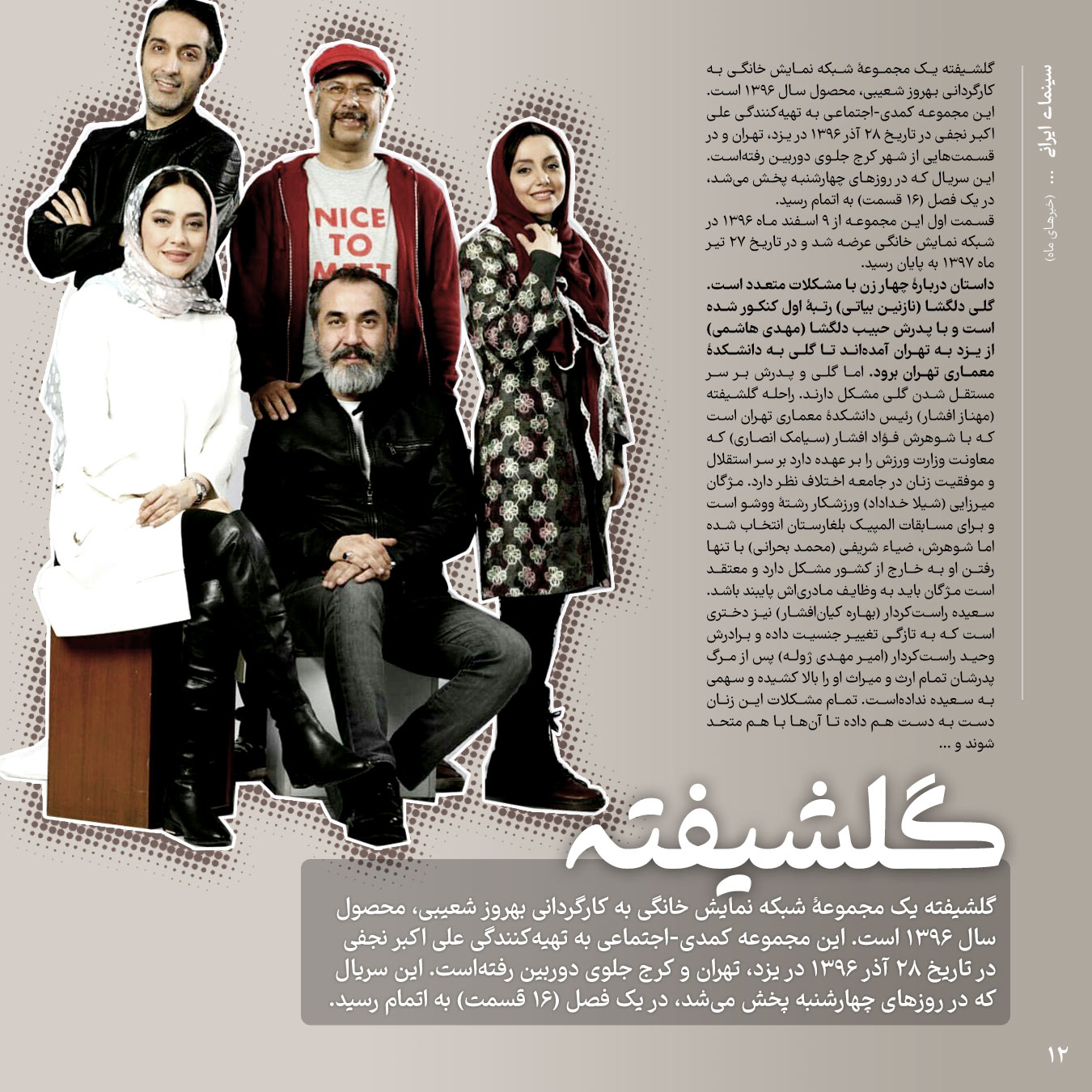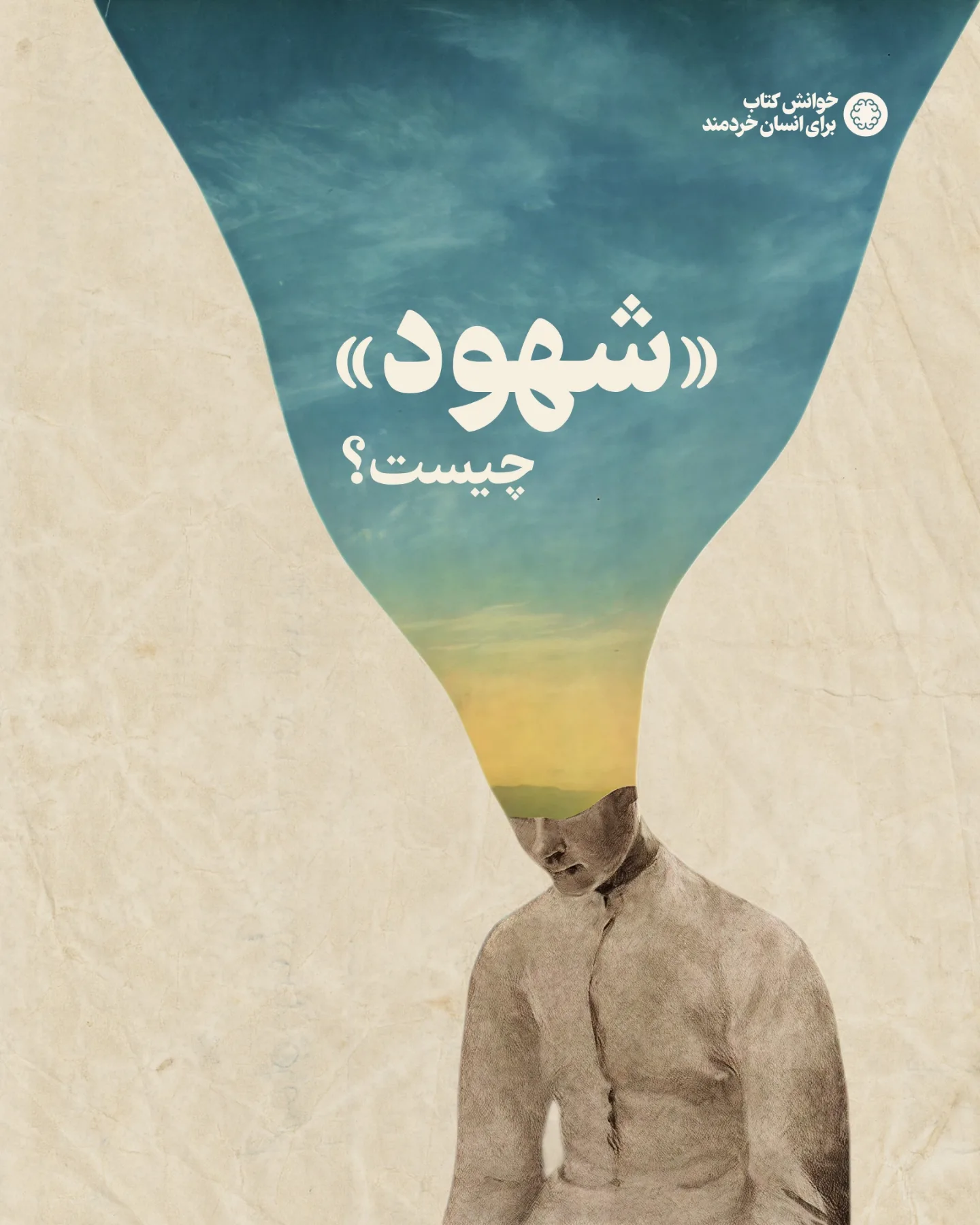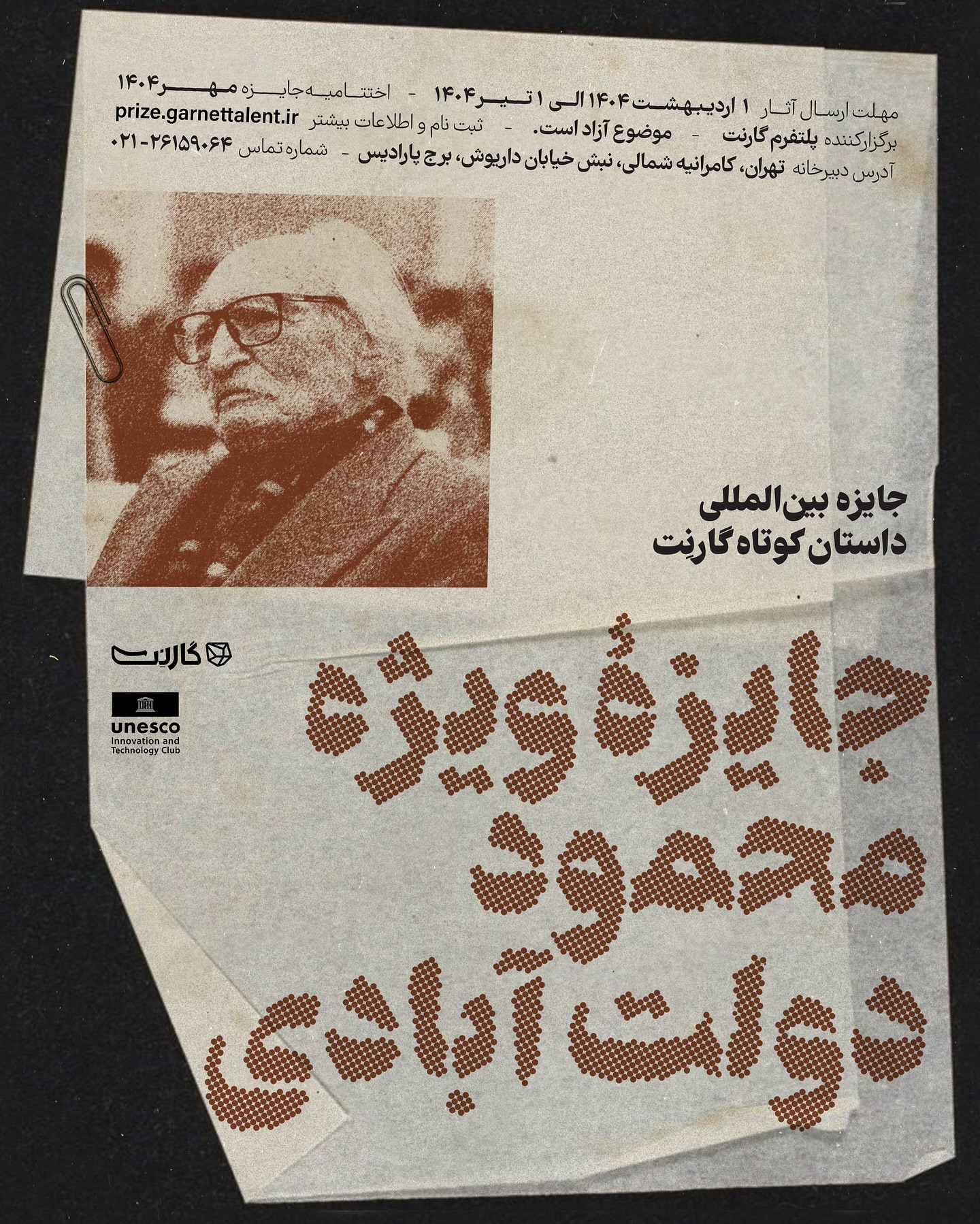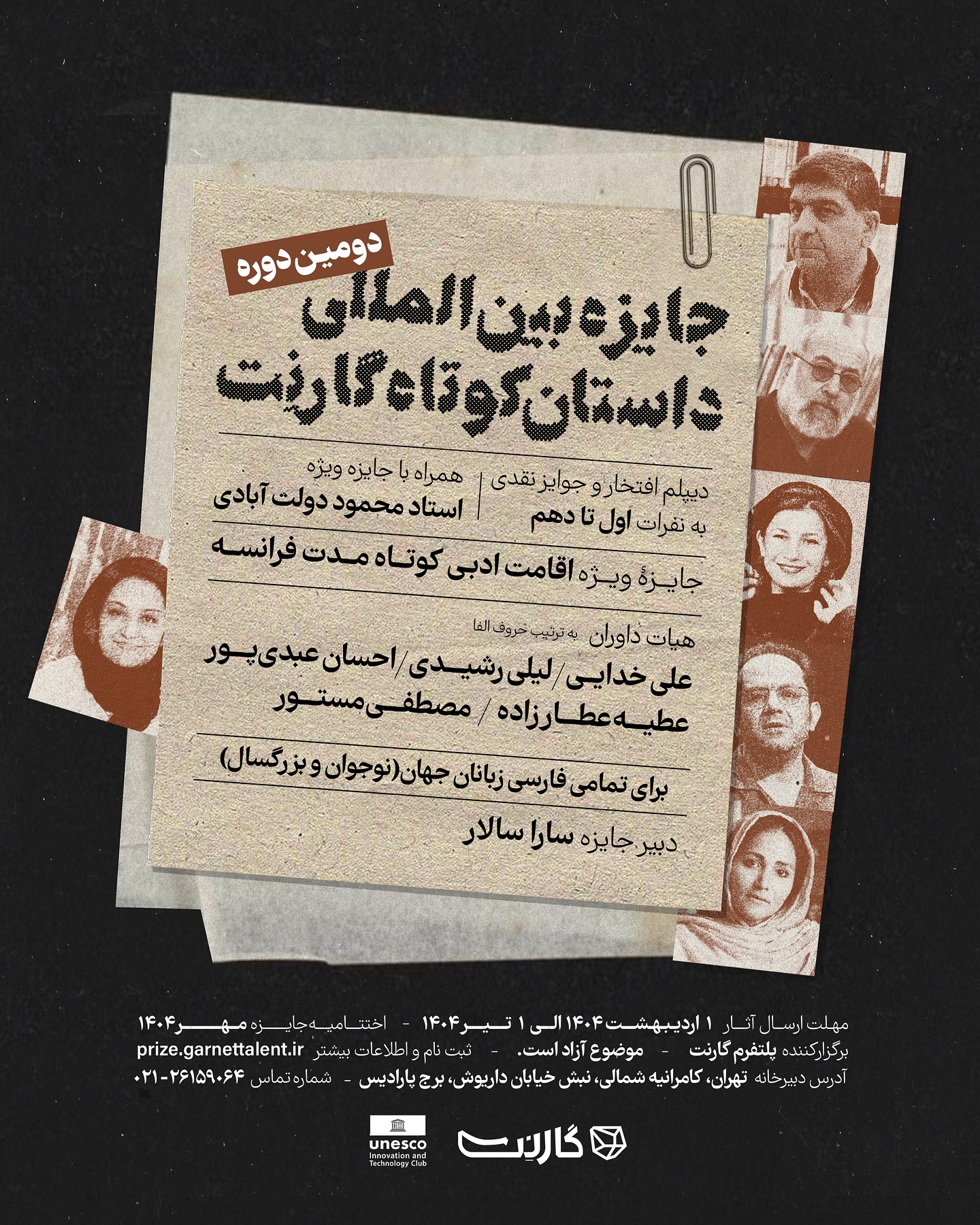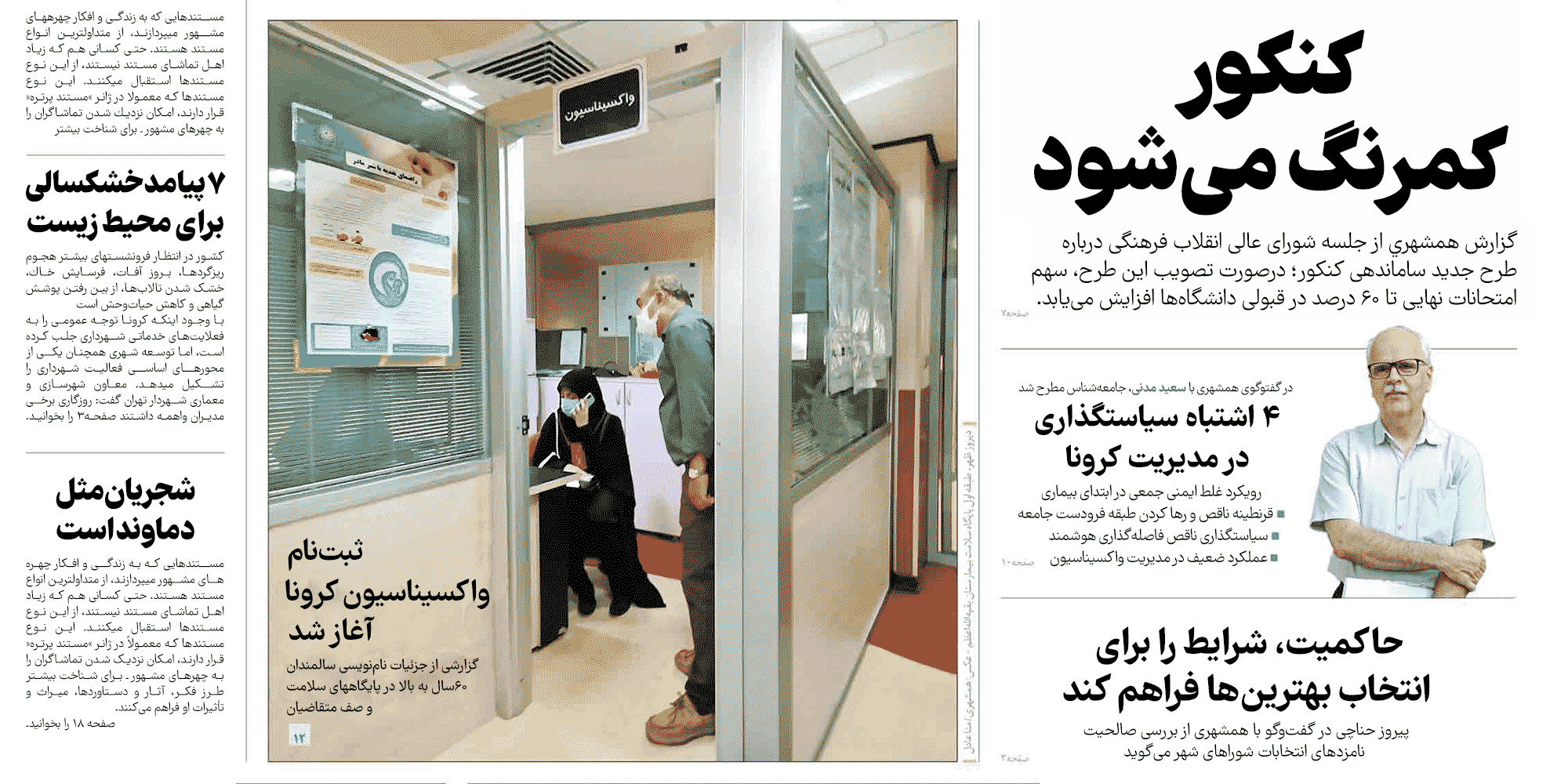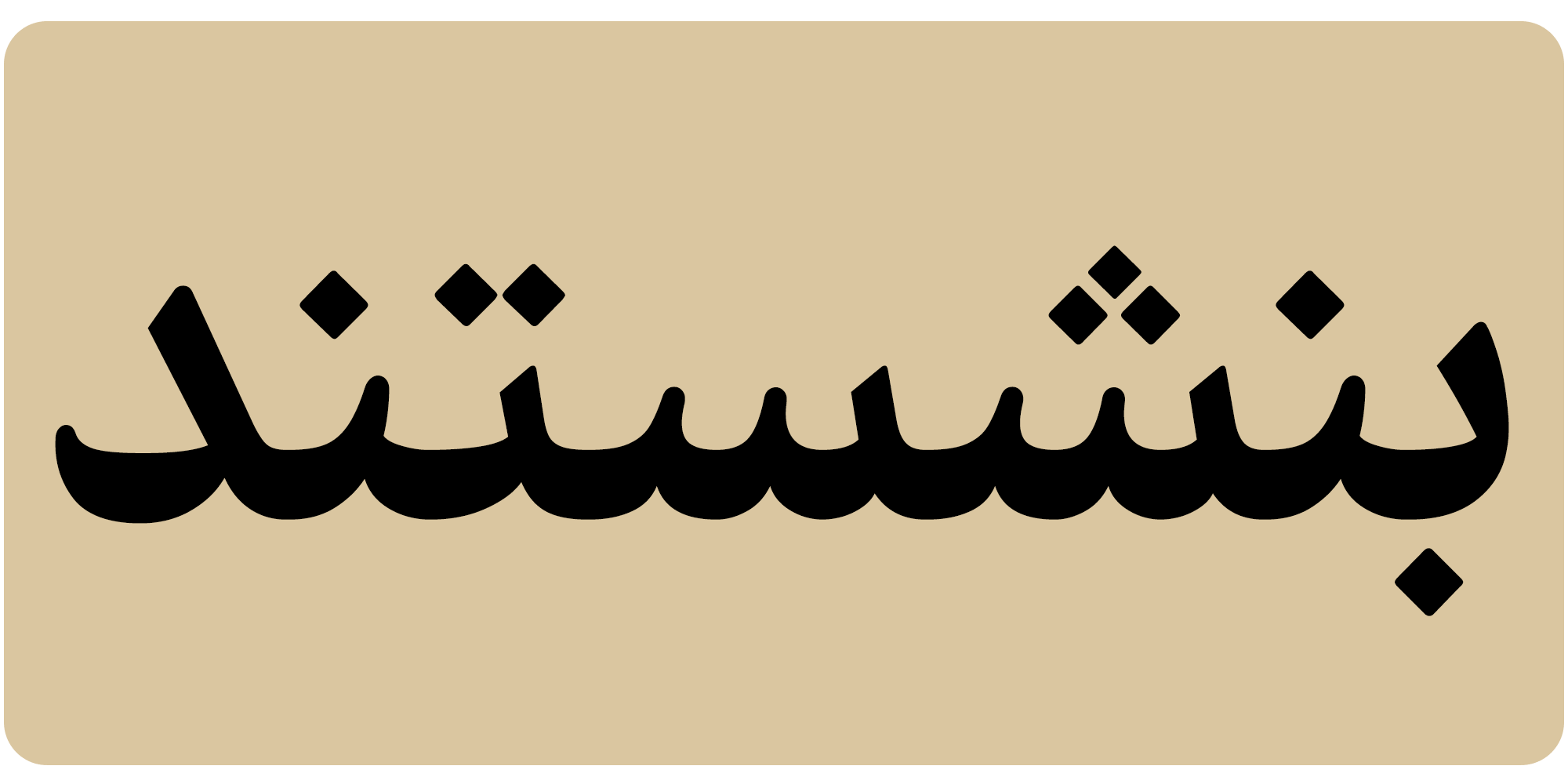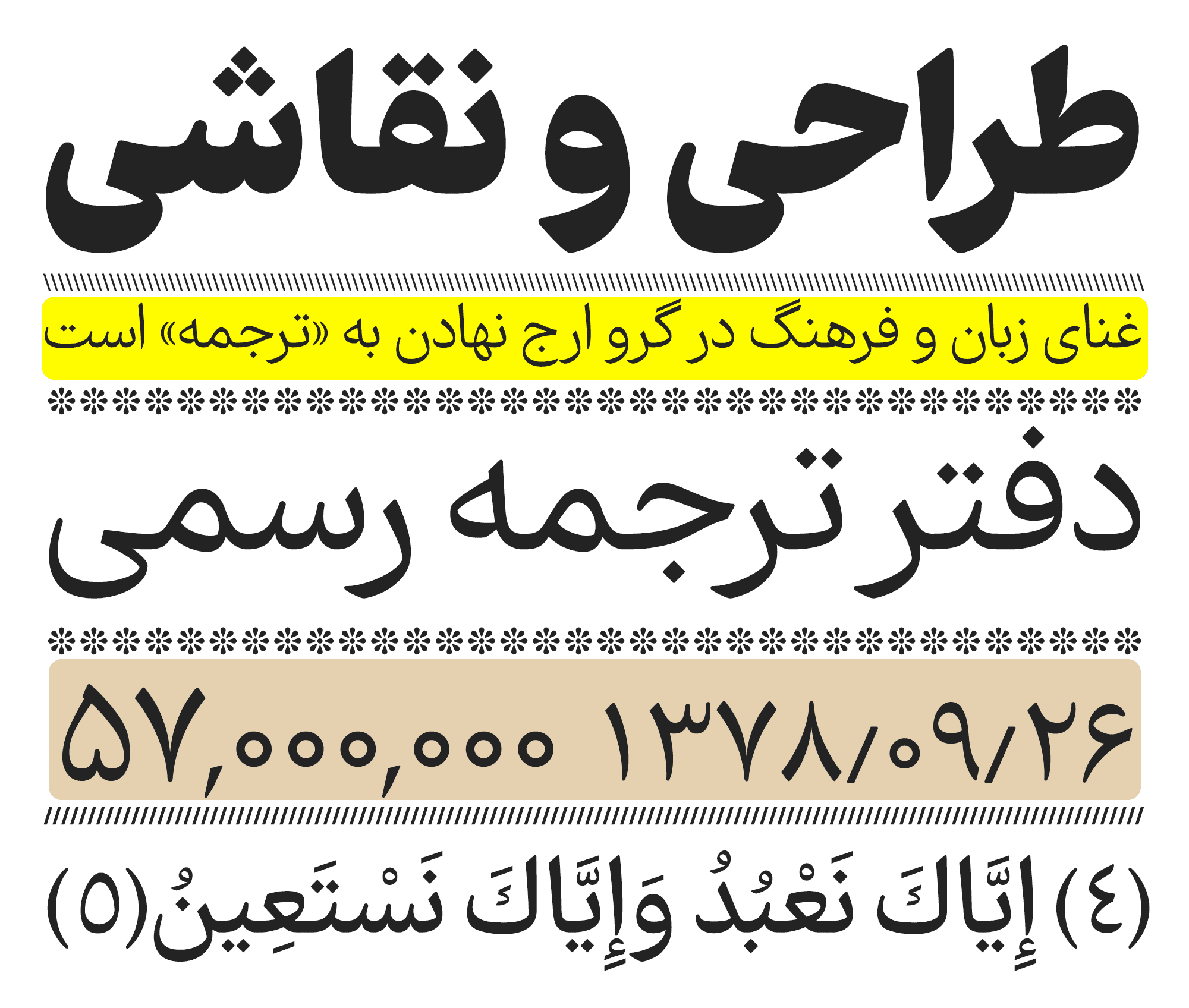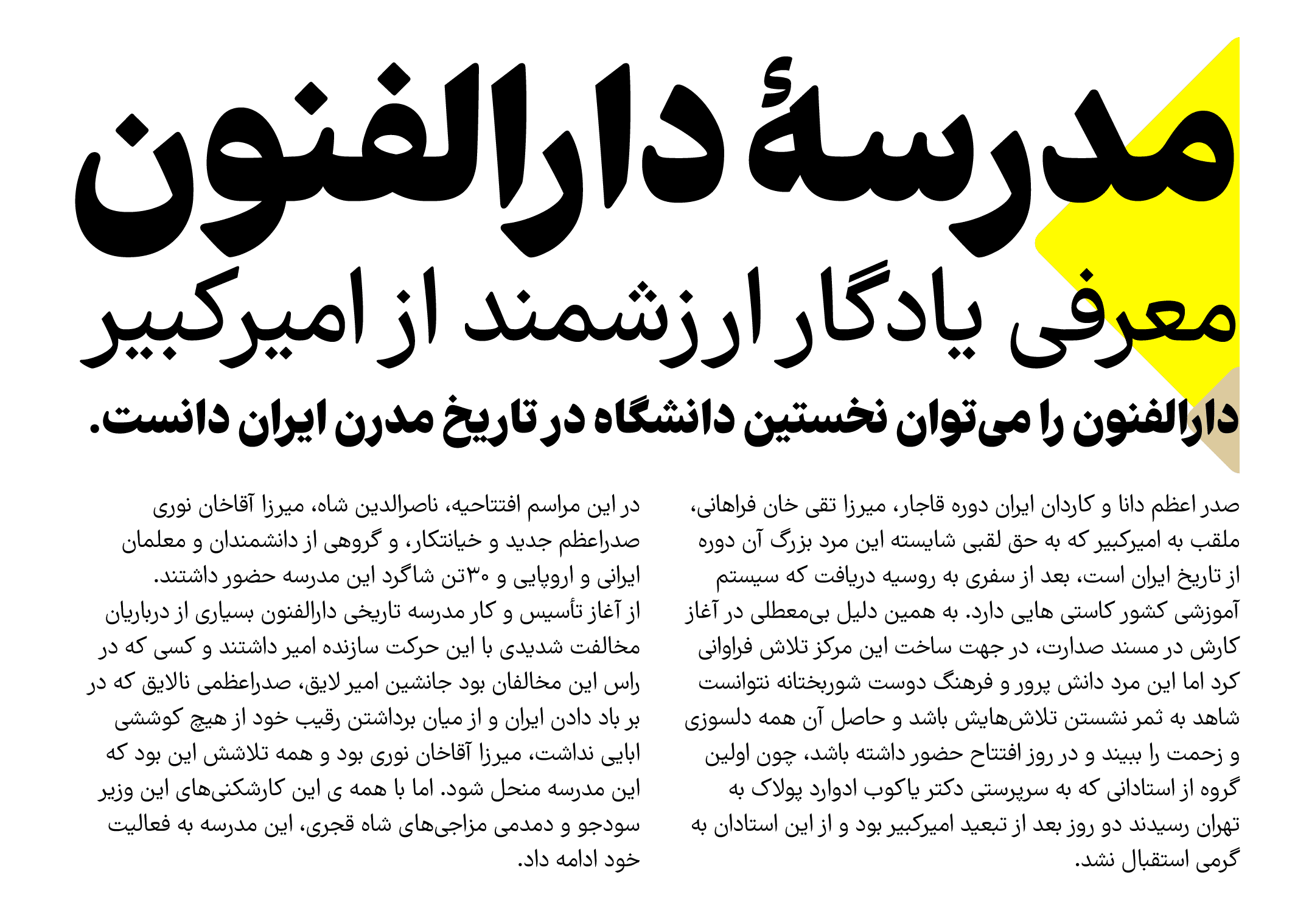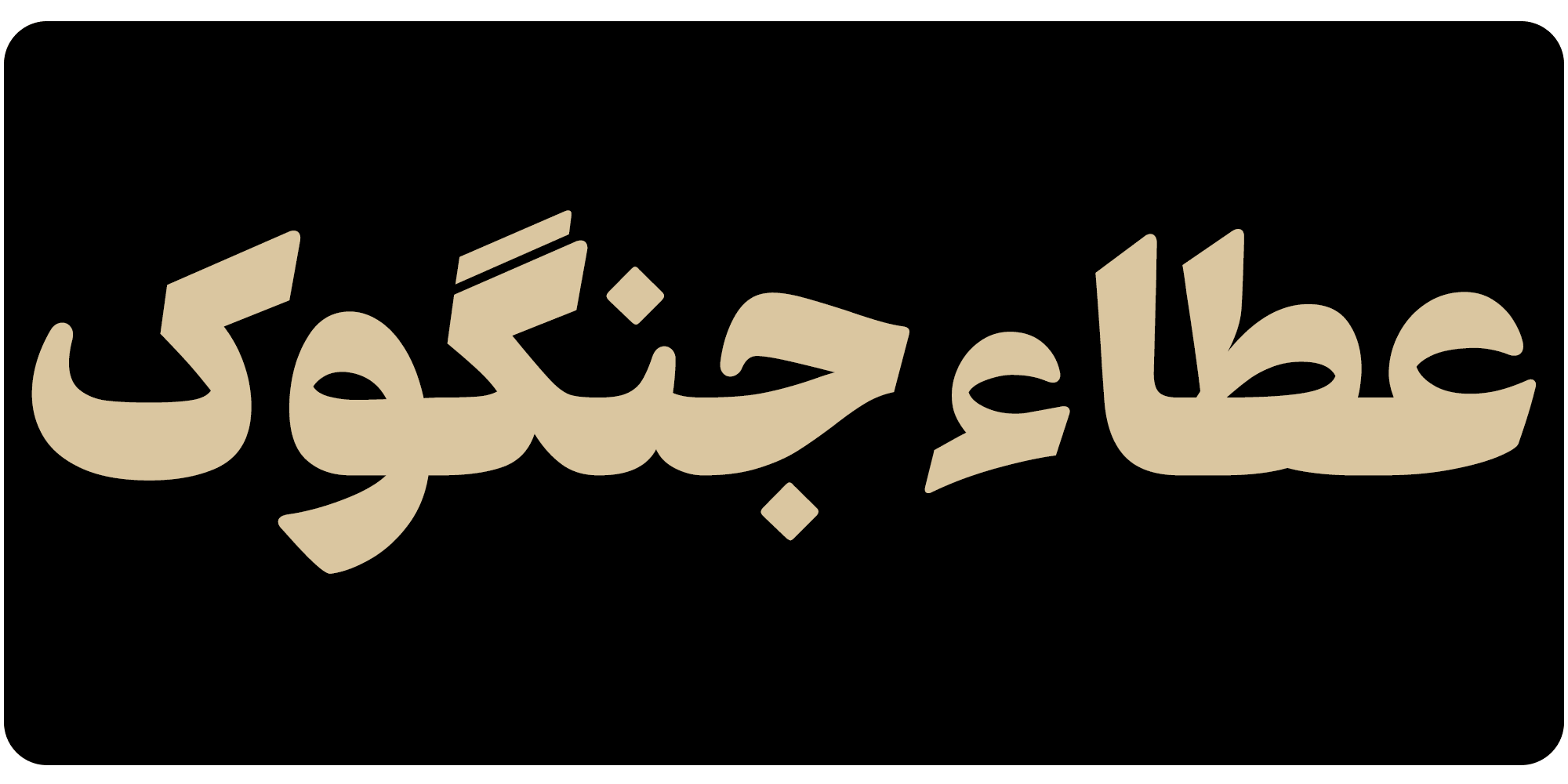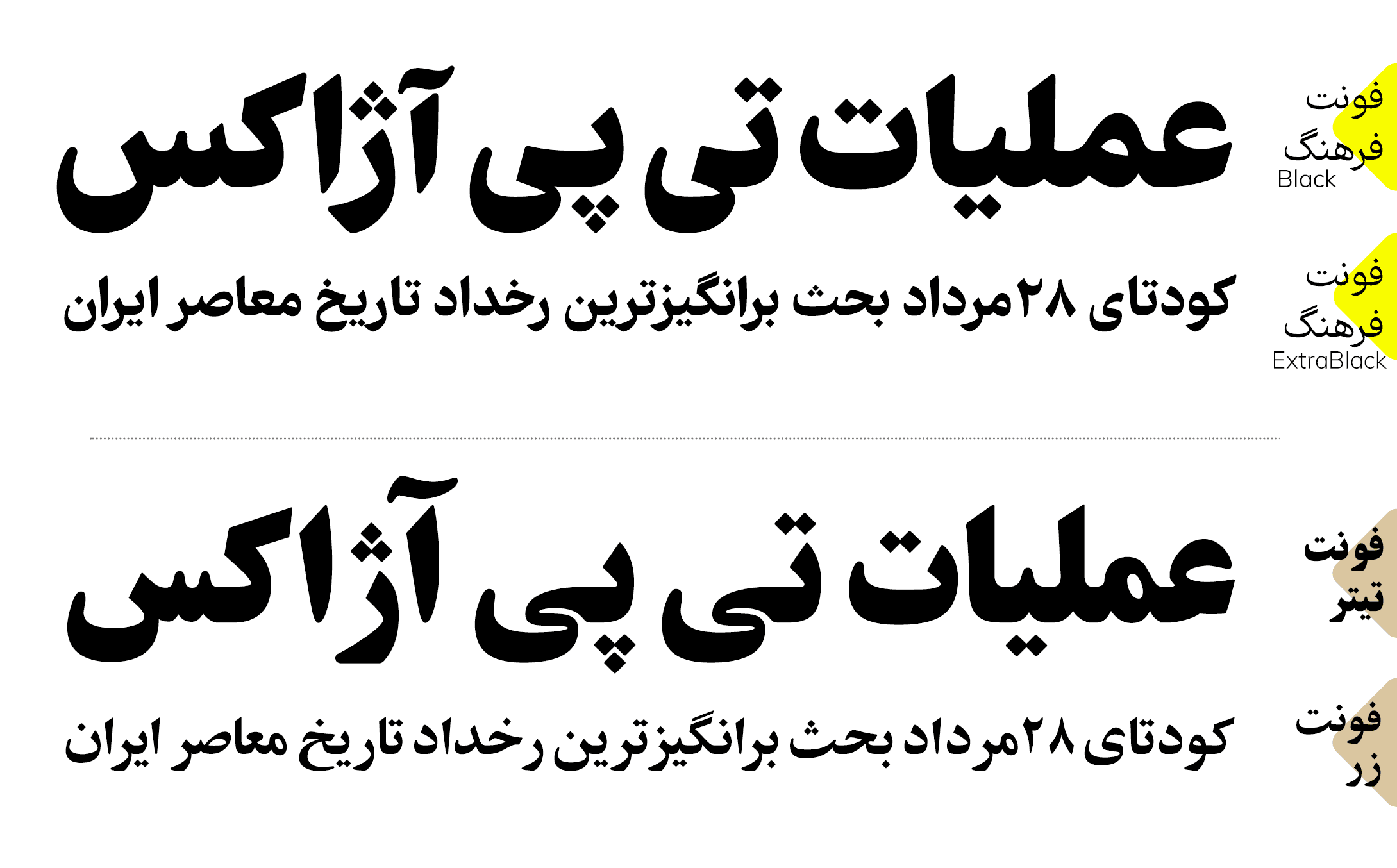
- این فونت از زبان فارسی، عربی، کردی، اردو و انگلیسی پشتیبانی میکند.
تنوع وزنها در فونت فرهنگ
در فونت فرهنگ شما طیف کاملی از ۹ وزن را در اختیار دارید و این وزنها در ۲ شکل نقطه در اختیار شما قرار دارد. نقطههای معمولی و نقطههای گرد و پیوسته.
چینش دقیق نقطهها و دندانهها
به دلیل وجود محدودیتهای حروفچینی در دستگاههای اولیه چاپ جای نقطهها مایل به راست است و این رسم در فونتهای دیجیتال نیز باقی مانده است.
در فونت فرهنگ Farhang نقطهها در جای درست خود یعنی زیر حرف مربوط به آن قرار دارند.
حروفی مانند ب ب ت ت پ پ ث ث ن ن ی ی س س ش ش گروه پر جمعیت خط فارسی هستند که شکل کاملا مشابهی دارند. چشم تنها با تشخیص نقطهها آنها را از هم تشخیص میدهد.
در فونت فرهنگ Farhang هر دندانه با توجه به حروف قبل و بعد خود جای نقطهٔ خود را طوری تعیین میکند تا نهایت نظم و زیبایی در شکل کلمات بدست آید.
در فونت فرهنگ نقطهها بصورت برنامهریزی شده در محل ایدهآل قرار می گیرند. بدون اینکه عرض حروف زیادتر شود یا فضای خالی بیش از حد پدید آید.
حروف جایگزین
اکثر حروفی که دوست دارید در فونت به عنوان جایگزین انتخابی استفاده کنید (مثل ﮧ ﮩ مدل نستعلیق و ے معکوس) حروف زبان اردو هستند. از آنجا که فونت فرهنگ این حروف اردو را دارد امکان استفاده از آنها در کیبورد فارسی نیز برای شما فراهم شده است. این حروف جایگزین را طبق راهنما و به راحتی در هر محیطی میتوانید تایپ کنید.
وریبل فونت فرهنگ
فونت متغیر (Variable Font) این امکان را میدهد که همهی وزنها را در قالب یک فایل فونت در اختیار داشته باشید.
در نسخه جدید فونت فرهنگ فقط متغیر وزن وجود دارد اما دیگر متغیرها در قالب نسخه قبلی در بسته در دسترس است. (نسخه قبلی رفع اشکال شده است اما دیگر بهروزرسانی نخواهد شد)
Sharp : این متغیر لبه گرد حروف را زاویه دار میکند و از گردی و انحنای شکل حروف میکاهد.
Serif : این متغیر زائدههای تزئینی مرسوم در خوشنویسی نسخ را به بعضی حروف اضافه میکند.
Kashidah : این متغیر میتواند در کلمات کشیدگی عرضی ایجاد کند.
در نسخه جدید فونت فرهنگ همه حالتهای اعداد را در یک فایل میتوانید استفاده کنید. برای این کار از فیچرهای اپنتاپ برای جایگزینی اعداد استفاده میشود.
هماهنگی با حروف لاتین
در فونت فرهنگ از فونت آزاد Muli استفاده شده است و سعی شده است سایز حروف همراه با افزایش و کاهش وزن تغییر نکند.
مقایسه با فونتهای مطبوعاتی رایج
در طراحی فونت فرهنگ سعی شده است سبک رایج در فونتهای نسخ ایرانی حفظ شود از این رو مقایسه با فونتهای تیتر، نازنین و زر میتواند مفید باشد.